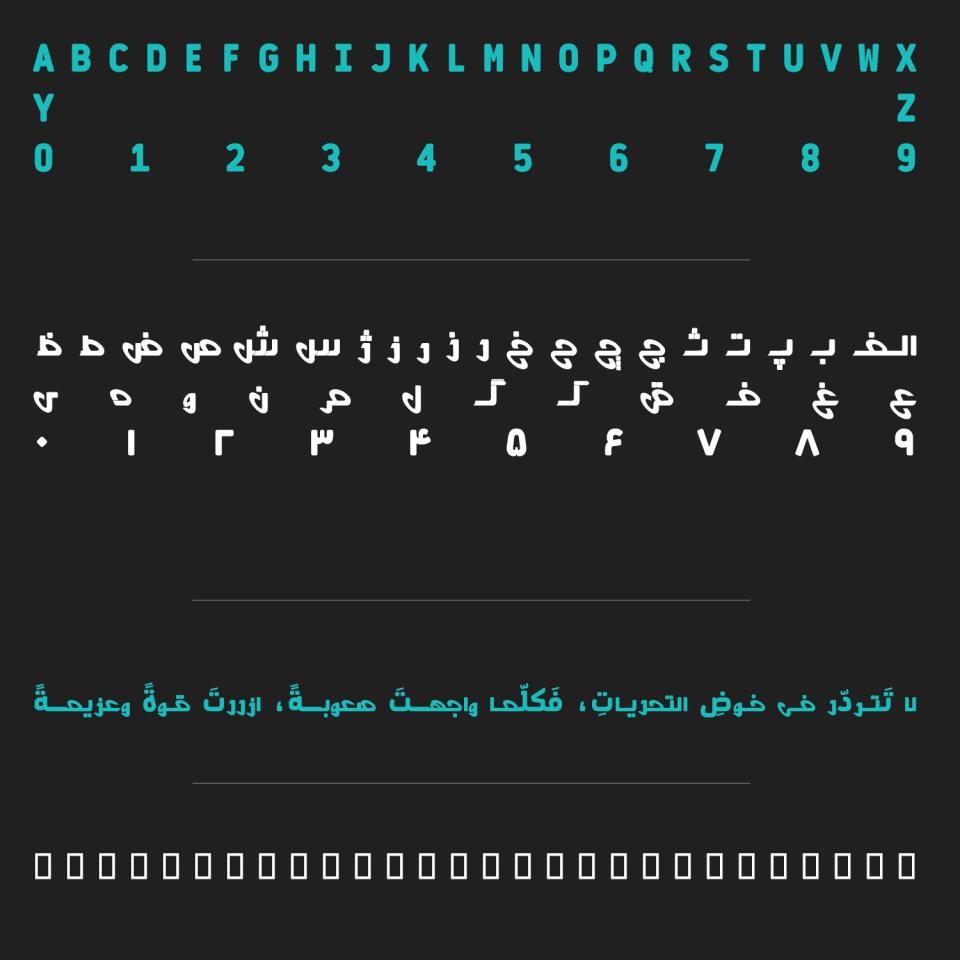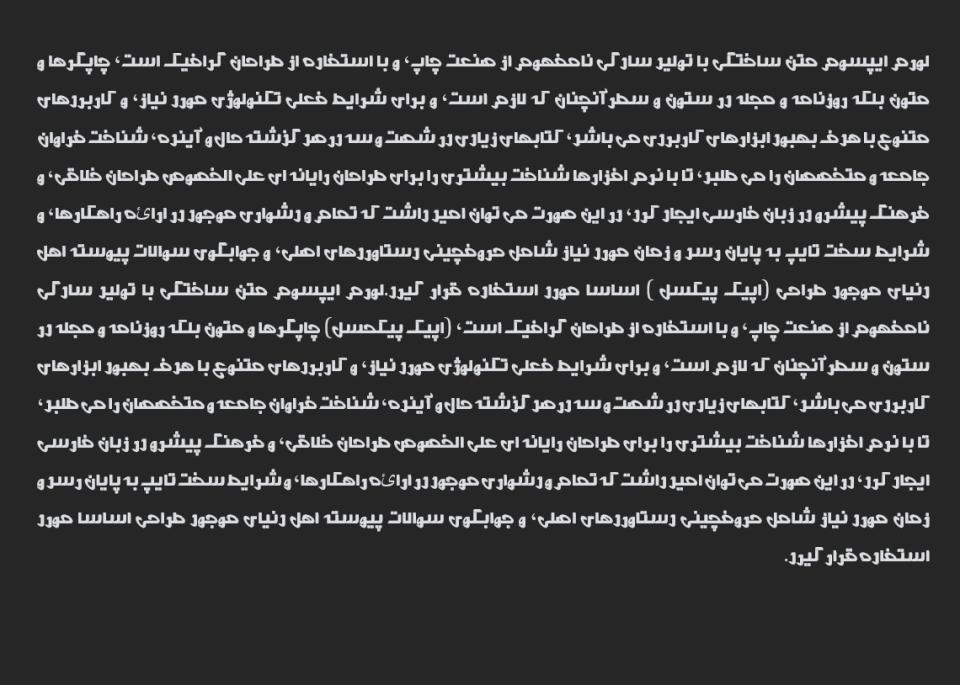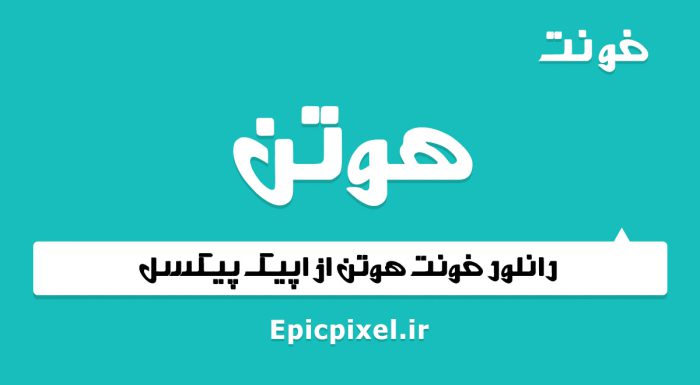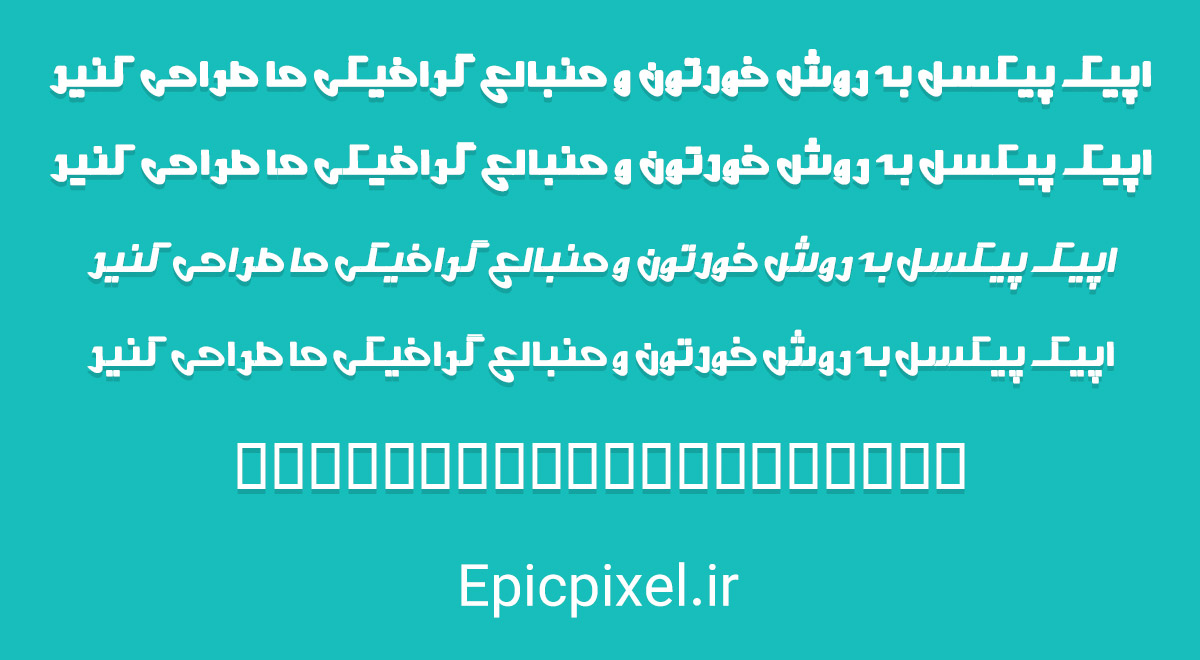
فونت هوتن فارسی
فونت هوتن، یک انتخاب عالی برای کسانی است که به دنبال ظاهری ساده و در عین حال شیک در طراحی های خود هستند. این فونت، با خطوطی نرم و خوانا، هم برای متن های طولانی و هم عناوین کوتاه، به خوبی جواب می دهد. انعطاف پذیری بالای هوتن به شما این امکان را می دهد که آن را در طیف وسیعی از پروژه ها، از طراحی وب سایت و لوگو گرفته تا چاپ و تبلیغات، به کار ببرید و به راحتی با سایر عناصر طراحی ترکیب کنید.
یکی از ویژگی های برجسته این فونت، هماهنگی عالی آن با دیگر فونت ها و عناصر گرافیکی است که به شما در خلق طرح های یکپارچه و جذاب کمک می کند. اگرچه هوتن بیشتر برای متن های مدرن و مینیمال مناسب است، اما شاید برای طرح های سنتی یا بسیار پر زرق و برق، انتخاب ایده آلی نباشد. با این حال، سادگی و چندمنظوره بودن آن، هوتن را به گزینه ای مطمئن و کاربردی برای بیشتر طراحان تبدیل کرده است. این فونت به صورت رایگان در دسترس است و می توانید به راحتی آن را دانلود و در پروژه های خود استفاده کنید.